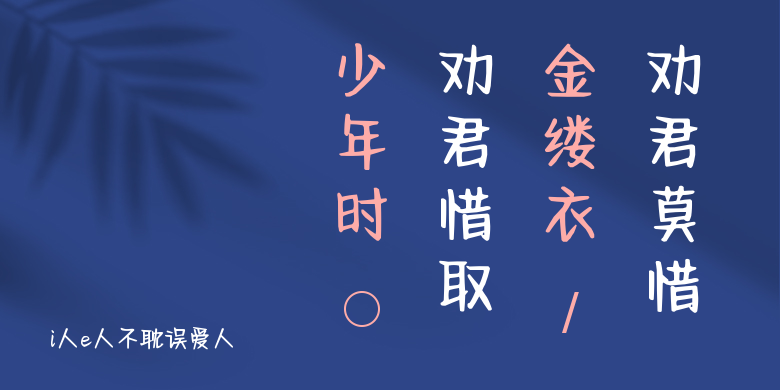
i人e人不耽误爱人
i人e人不耽误爱人,这款字体结构工整、笔画清晰,兼顾美观与易读性,适用于标题、正文、海报、包装、LOGO 等多种场景。字形优雅稳定,风格百搭耐看,适配日常排版与创意设计,让文字呈现更舒适、更具质感。i人e人不耽误爱人一笔一画,皆是细节,以均衡的比例、流畅的线条打造舒适视觉体验,字形端正大气,风格简约现代。无论是商业设计、品牌宣传还是日常排版,都能轻松驾驭,让文字更有格调与力量。i人e人不耽误爱人字体下载。